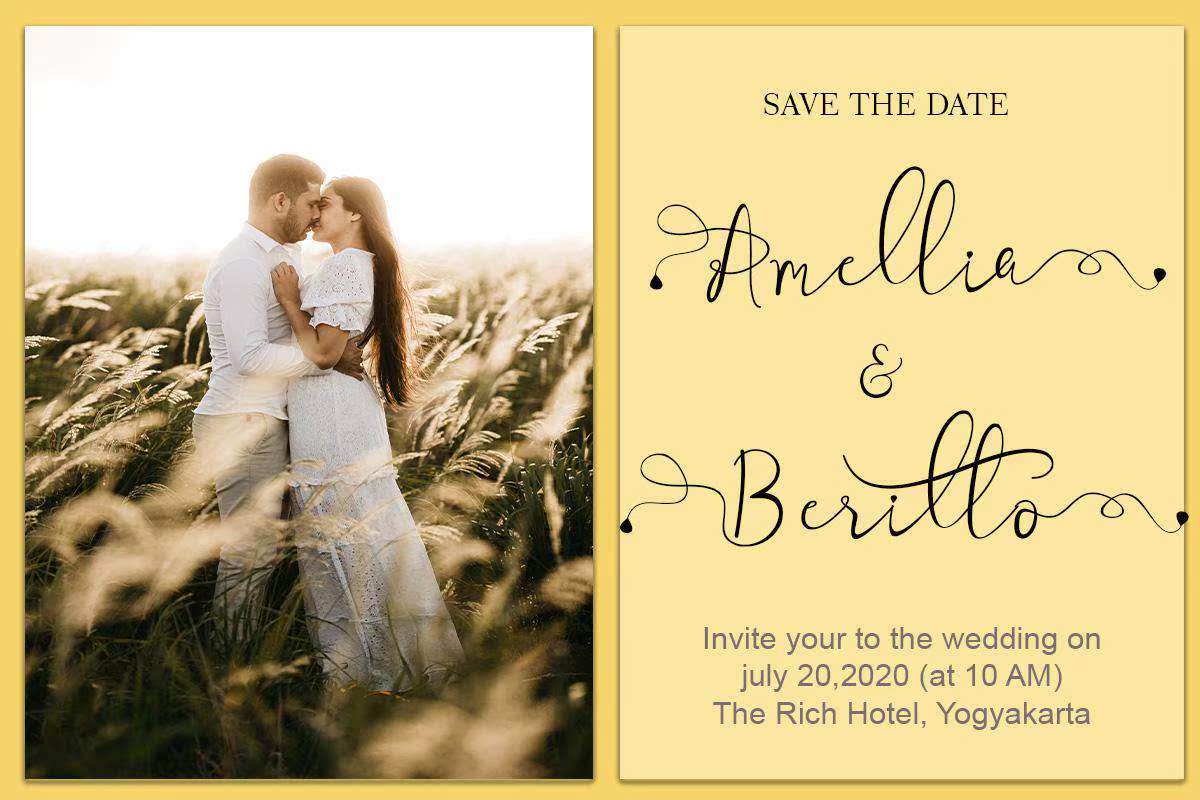
此款香水名为“Maretha”。Maretha非常美丽且有说服力。此款香水是一款现代化的装饰艺术,能够完美地装饰您的作品。此款香水特别适用于婚礼、婚礼摄影、婚礼庆典、品牌推广、美丽的婚礼。它非常适合为情侣打造浪漫情调,引用精华以美化您的旅行。运河会宣传您的产品或业务。此款香水名为“Maretha”。Maretha非常美丽、合法。此款香水是一款现代化的智能手机,能够完美地美化您的工作。此款香水特别适用于婚礼、婚礼摄影、婚礼宣传、品牌推广、美丽的婚礼。它非常适合打造情侣间的浪漫情调,请引用要点,以便美化您的旅行。运河会宣传您的产品或业务。